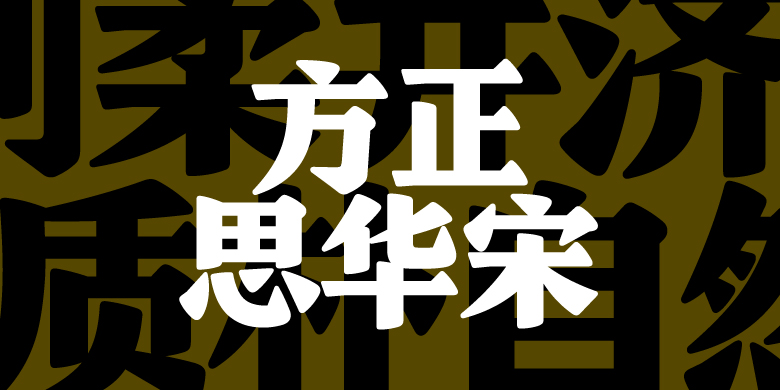
方正思华宋
吕方俏
宋体
这是一款为标题而设计的粗体字。其最大的特点是拥有结实的横画,用以区别和打破传统宋体字感横画细致的样貌。在笔画造型的修饰处尽量克制简化,笔画清晰醒目、易识别,问架结构布局结实可靠。另外在字形的起笔和收笔处做圆角处理,整体字感给人以大气、温润、和谐、友善、方整、醒目的视觉面貌。适用于文化标题、推广语、字幕、导视、海报、产品包装等场景上使用。